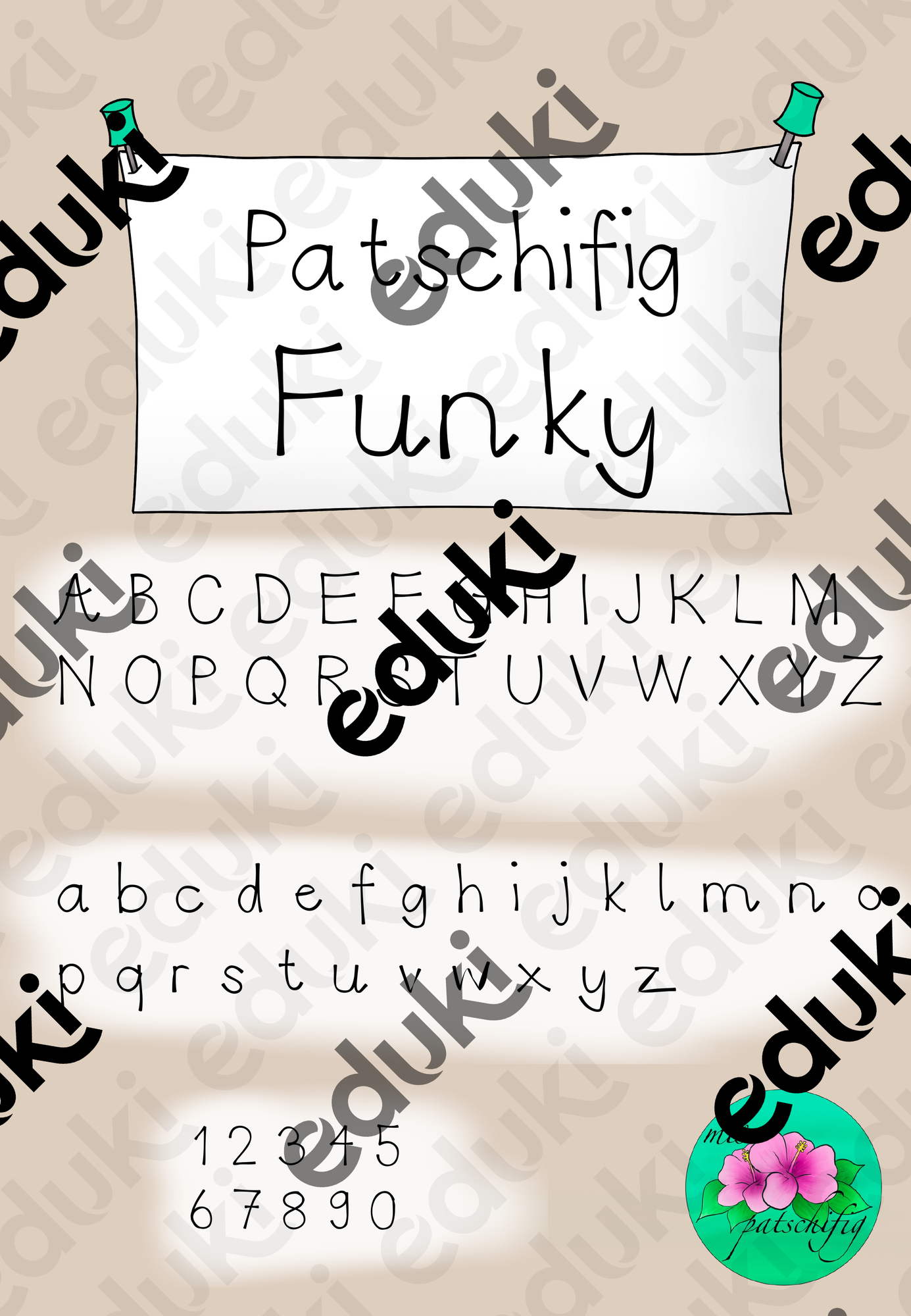
Patschifig Funky Font: Handschrift für private und kommerzielle Nutzung
Bist du auf der Suche nach einer stilvollen Handschrift, die du sowohl privat als auch kommerziell verwenden kannst? Die Patschifig Funky Font bietet dir genau das! Diese Schrift ist vielseitig einsetzbar und verleiht deinen Projekten eine persönliche und ansprechende Note – egal, ob für Unterrichtsmaterialien, kreative Designs oder geschäftliche Zwecke.
Das Besondere an der Patschifig Funky Font: